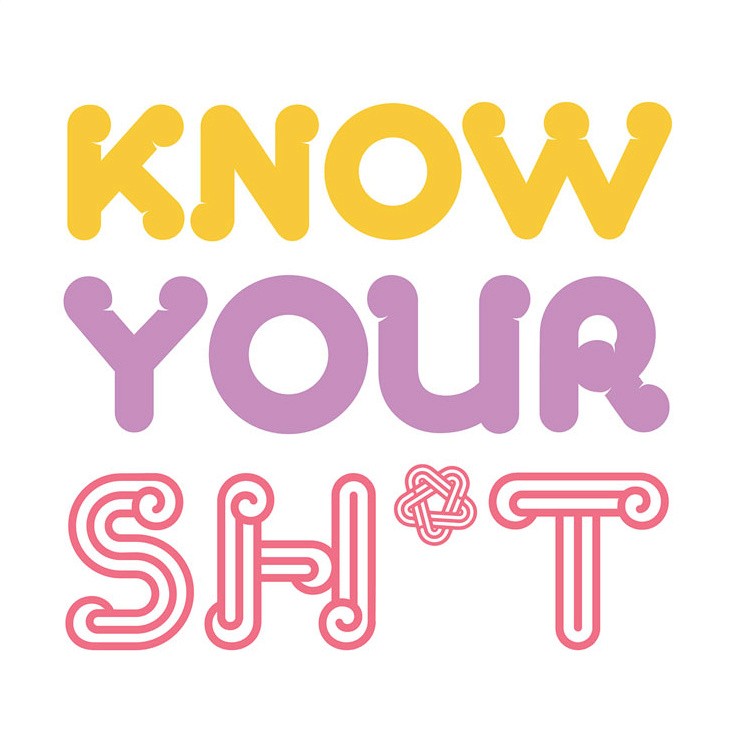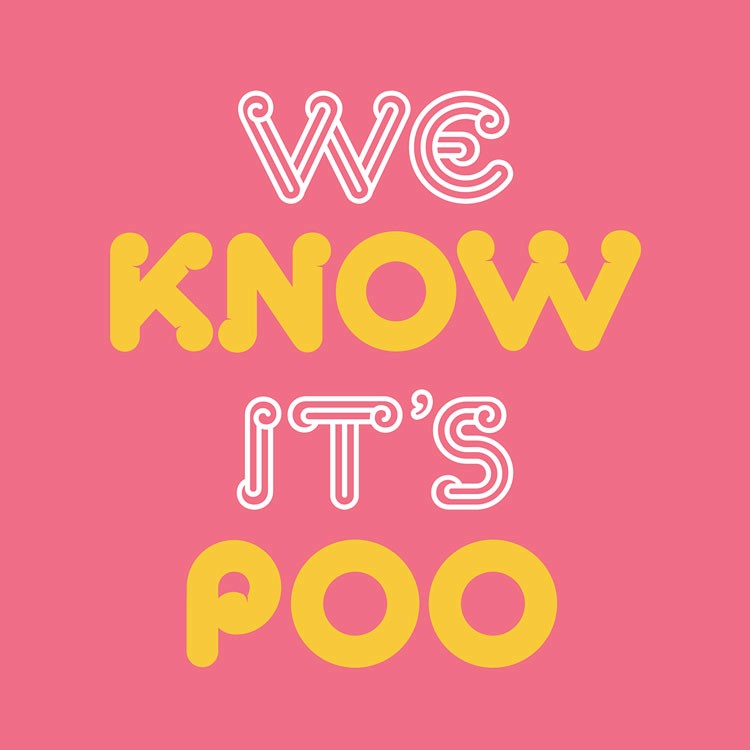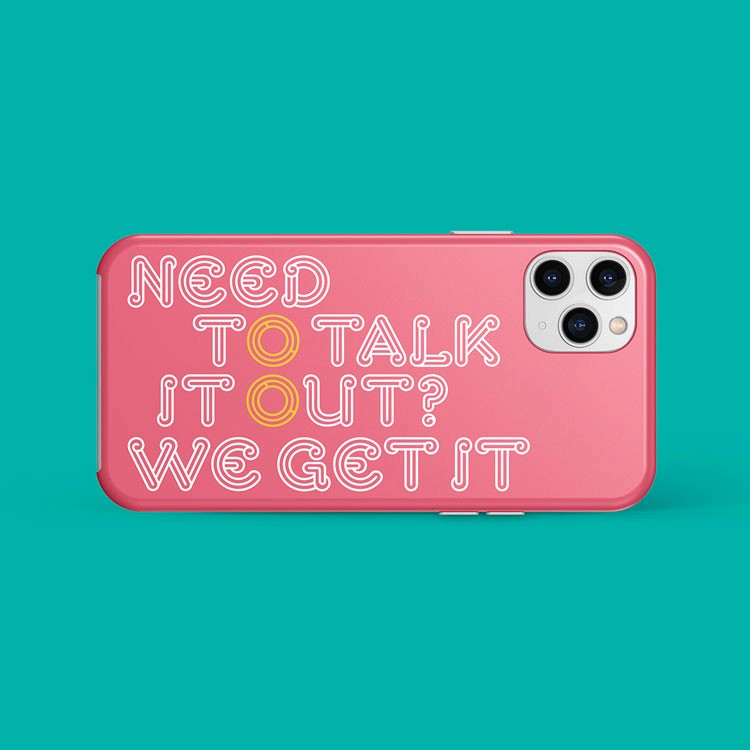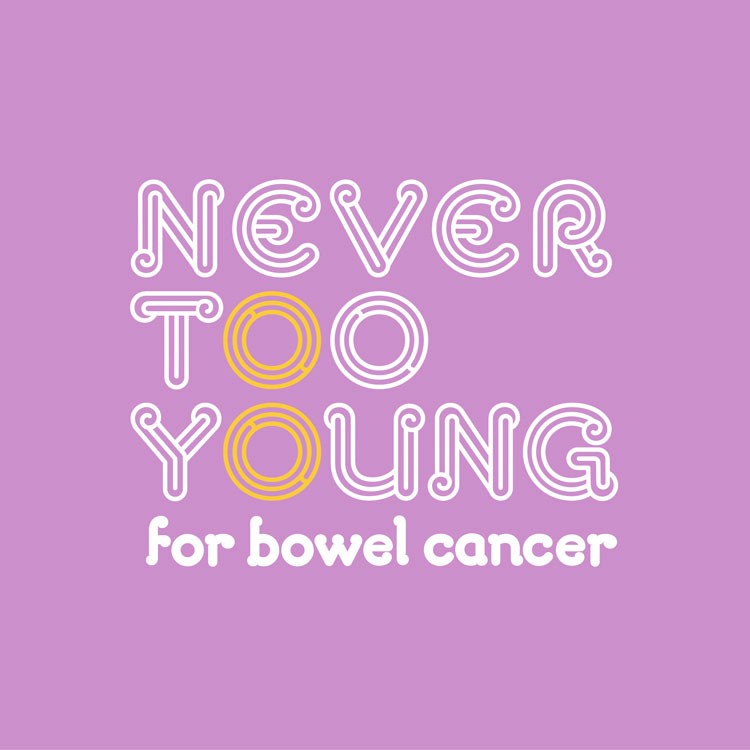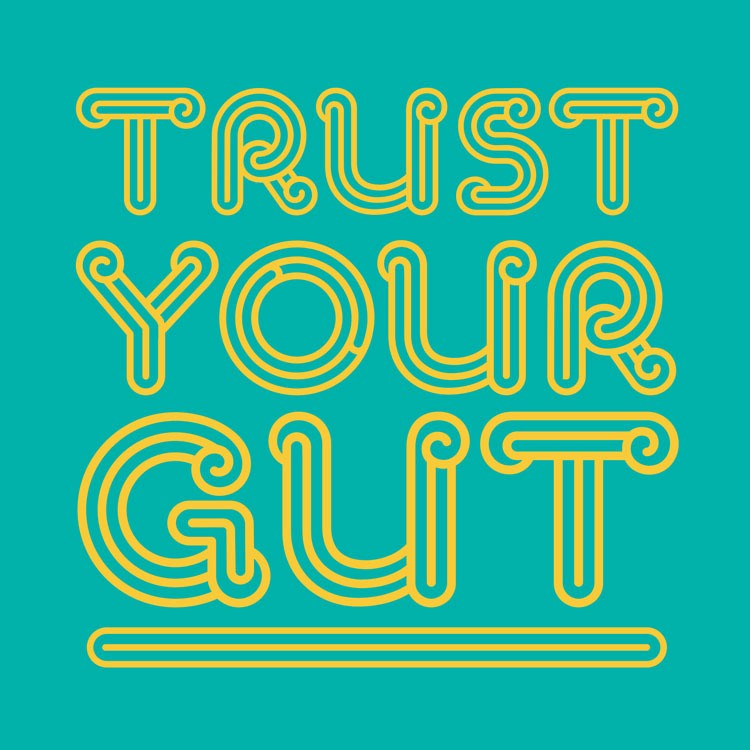
“A visually challenging typeface”- Typerface thách thức trực quan
Never Too Young là tên bộ nhận diện thương hiệu được thực hiện bởi Taxi Studio, dành cho tổ chức từ thiện do Sophia Sangchi thành lập để nâng cao nhận thức về bệnh ung thư ruột ở những người trẻ tuổiCó một quan niệm phổ biến nhưng chưa đúng rằng ung thư ruột là một căn bệnh chỉ ảnh hưởng đến những người lớn tuổi. Thực tế, có khoảng 2.500 người dưới 50 tuổi được chẩn đoán mắc căn bệnh này ở Anh mỗi năm, và Sophia Sangchi là một trong số những người trẻ mắc ung thư ruột giai đoạn 4.
“A visually challenging typeface”- Typerface thách thức trực quanTiêu điểm của dự án này chính là typerface được đặt theo tên người sáng lập: Sophia Bold và Sophia Display, nhà thiết kế Tom Lane đã “đổ trái tim và cả tâm hồn mình” để tạo ra typerface với cảm hứng từ RUỘT, với những nét xoắn và mỗi chữ cái đều xuất hiện 2 chữ “o” với dụng ý mô phỏng đầu ruột già, mong muốn bộ nhận diện có thể thu hút sự chú ý và thúc đẩy nhận thức của cộng đồng
“Know your sh*t”Typerface Sophia Bold và Sophia Display xuất hiện xuyên suốt trên các phương tiện truyền thông và các sản phẩm của thương hiệu như áo thun, túi xáchViệc sử dụng các cụm từ “Know your sh*t”, “Trust your gut” và “We know it’s poo” trong truyền thông thương hiệu để truyền tải thông điệp và sự thật về căn bệnh ung thư ruột một cách nhẹ nhàng, vui nhộn hơn để thúc đẩy nhận thức bảo vệ sức khỏe của cộng đồng
“Unexpected” touchpointsSophia Bold và Sophia Display đều được sử dụng trong toàn bộ nhận dạng trong truyền thông thương hiệu, trên phương tiện truyền thông xã hội và các mặt hàng quảng cáo như túi xách và áo thun. Hơn thế nữa, để đến gần và trở nên thân thuộc hơn với khách hàng, họ lựa chọn thể hiện thương hiệu trên ốp lưng, giấy vệ sinh, và 1 số vật dụng thông dụng khác có thể sử dụng hàng ngày
Tóm lại: Typeface Sophia vẫn cho ta thấy được sự vui tươi và dễ thương nó cũng là mục tiêu khác mà Never Too Young hướng đến. Kết hợp với nội dung và thiết kế Never Too Young gây được sự chú ý tới khán giả nhỏ tuổi, bằng cách mang đến cho họ những sự thật một cách dí dỏm, cùng lúc đó thu hút những tình nguyện viên, mạnh thường quân mong muốn hỗ trợ cho những bệnh nhân bị ung thư ruột.